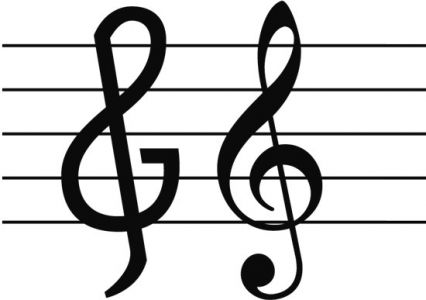
hat jemand von Euch einen Schimmer wo man Noten-Fonts herbekommt?
Hat auch von Euch jemand schonmal Erfahrung beim Notensetzen gesammelt?
Auf der Typo 2007 gab es einen Vortrag von Werner J. Wolff zum
Thema »500 Jahre Notendruck und Notengrafik«.
Das Fazit zuerst: Werner J. Wolff schaffte es mit seinem Vortrag
über den Notensatz für Klassik-Partituren selbst eingefleischte
Typografen-Nerds zu beeindrucken. »Mann, die haben es ja noch
schwerer als wir!«, hörte ich Jürgen Siebert, den Chef vom Fontshop,
hinter mir sagen. Die wenigen Gäste, die sich bei dem skurrilen
Vortrag über »500 Jahre Notendruck« zusammenfanden – sie alle
hatten Mitleid mit Werner J. Wolff.
Wenn es um schönen Notensatz mit klassischer Notenstich-Anmutung geht, ist die Open-Source-Software Lillypond einen Blick wert, die auch sonst mit den kommerziellen anbietern (Sibelius, Cubase usw.) mithalten kann. Allerdings ist die Bedienung da TeX-basiert nicht eben intuitiv, die Midi-Ausgabe etwas aufwendig. Bei Rosegarden liegt der Fokus eher auf Komosition, die Bedienung ist dafür einfacher.
Ich habe selber kaum Noten gesetzt, allerdings viele selbst zusammengestümperte Noten bekommen. An die TeX/LaTeX-basierten Systeme kommt kaum etwas von dem heran, was man sonst so bekommt. Das betrifft vorallem anwenderorientiertes Denken, also zum Beispiel, bekomme ich einen Seitenumbruch mitten in einer Passage, wo man überhaupt nicht blättern kann, werden bei Texten in Singstimmen die Silben ordentlich dargestellt und gebrochen etc. Die LaTeX-Module beherrschen das von Haus aus schon ganz gut und mit etwas feinerer Abstimmung lassen sich ganz ausgezeichnete Ergebnisse erzielen, während viele kommerzielle Programme weit hinterher hinken. Notensatz erfordert definitiv ein völlig anderes konzeptionelles Denken, da hier die »Leseabläufe« komplett andere Ansprüche haben als beim Lesen von einfachen Texten. Während bei Lesetexten ein »falscher« Umbruch den Text unklar werden läßt, kann ein Umbruch an falscher Stelle Noten schlicht und einfach **komplett* unbrauchbar werden lassen.
Bis vor wenigen Jahren gab es noch einen echten Könner, der Noten gestochen hat. Bei Bärenreiter, wenn ich mich recht entsinne. An sowas kommen Computersysteme bei weitem nicht ran! Aber mittlerweile ist das wohl komplett ausgestorben.
Ungeübt Notensatz machen, kann nur schiefgehen.
Da kann ich nur heftigst zustimmen. Und selbst von den professionellen Verlagen bekommt man vielfach Mist. Es ist ein Trauerspiel! :shock:
Es geht um eine einzelne Seite, die ohne Kapriolen auskommt.
Für ein Kinderlied. Aber ich würd's schon gern selbst machen, aus Überzeugung und zum Lernen.
Ich schau mir mal dieses Sibelius an,
Ich hab mal ein paar Notenzeilen mit Finale NotePad 2007 gesetzt, das ging richtig einfach und kost’ auch nix. Link zum Programm hat Ralf schon gepostet.
nur als hinweis und verpflichtung mir selbst gegenüber: Wenn nicht gerade Jahresendspurt wäre, würde ich an einer serifenlosen Notenschrift stricken. Hier ein kleiner Vorgeschmack, dauert aber noch was. Hier der G-Schlüssel mit erkennbarem G.
PS.: Eine serifenlose Notenschrift: interessant! Gibts da überhaupt Serifen? Wie auch immer, ein Hoch auf den Fortschritt! Ich bin gespannt auf weiteres von dieser Geschichte.
nur als hinweis und verpflichtung mir selbst gegenüber: Wenn nicht gerade Jahresendspurt wäre, würde ich an einer serifenlosen Notenschrift stricken. Hier ein kleiner Vorgeschmack, dauert aber noch was. Hier der G-Schlüssel mit erkennbarem G.
Hübsch! Aber Dir ist hoffentlich bewußt, daß der G-Schlüssel natürlich nichts mit dem Buchstaben »G« zu tun hat? Ungewohnte Notenformen sind zudem extrem schwer zu verdauen. Obwohl ich ja das Evangelische Kirchengesangbuch, welches von Herrn Willberg und seiner Frau gesetzt wurde, bezüglich des Layouts und der Typo vergöttere, habe ich mich mit den Notenformen, die er selber entwickelt hat, nie wirklich anfreunden können. Die sind zwar traditionell und stören auch nicht in eigentlichen Sinn, aber irgend etwas, was ich nicht klar definieren kann, ist »anders« und mir fällt das jedes Mal auf, wenn ich es mal wieder in die Finger bekomme.
Serifenlos sind ja die meisten Autographen, so wie das hier vom großen Ludwig:
Wäre das nicht ein wunderbarer Ausgangspunkt?
@ Norbert Pautner: genau da will ich hin. Die einzelne Note soll wieder mehr nach einem Punkt aussehen, nicht nach einer konstruierten Elipse.
@ CRudolph: Ich weiß, dass der Notenschlüssel nicht direkt vom G kommt, aber die Lage des g markiert, wenn auch etwas exaltiert. Das wollte ich wieder sichtbar werden lassen. Ob das der letzte Stand der Dinge ist, ist auch noch nicht sicher.
später mehr....